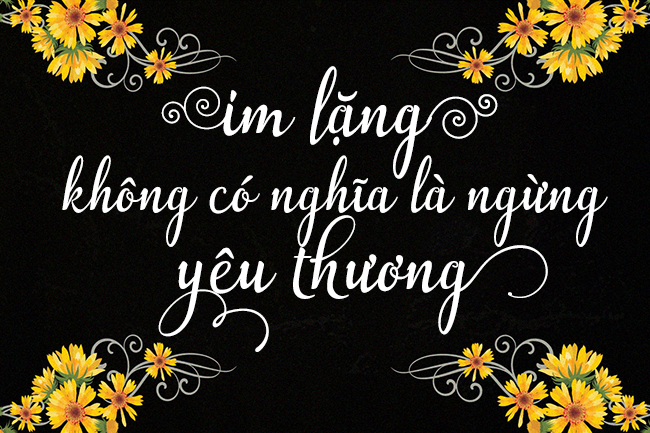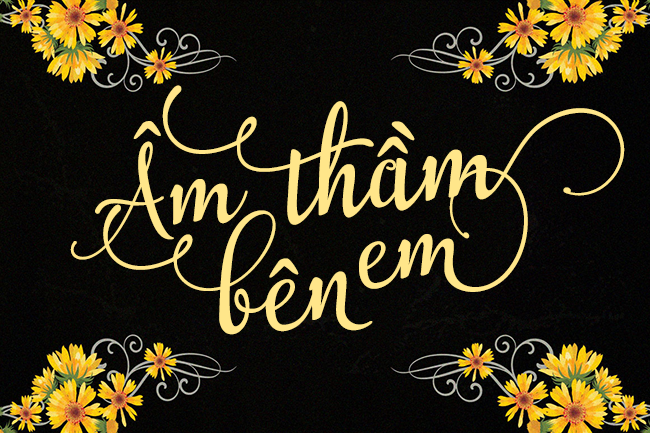
Aslang Barry là một kiểu chữ calligraphy hiện đại đầy cuốn hút, kết hợp giữa phong cách thư pháp cổ điển và hơi thở hiện đại. Font pha trộn từ copperplate đến kiểu chữ đương đại, với đường baseline uyển chuyển, mang lại cảm giác thanh lịch và hiện đại. Font có thể được sử dụng cho nhiều mục đích khác nhau như tiêu đề, chữ ký, logo, thiệp cưới, áo thun, letterhead, bảng hiệu, nhãn mác, ấn phẩm, poster, huy hiệu, v.v.